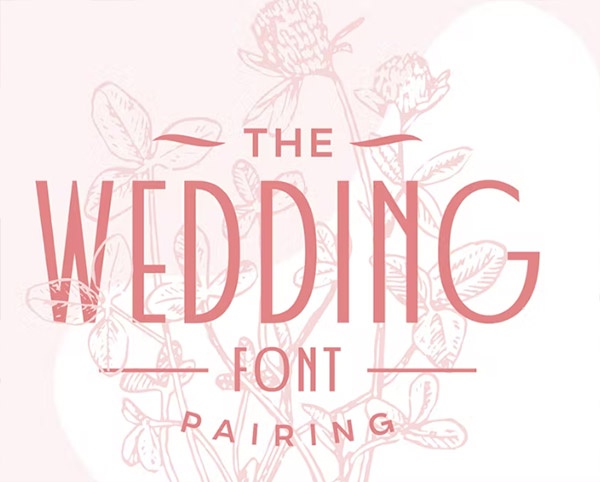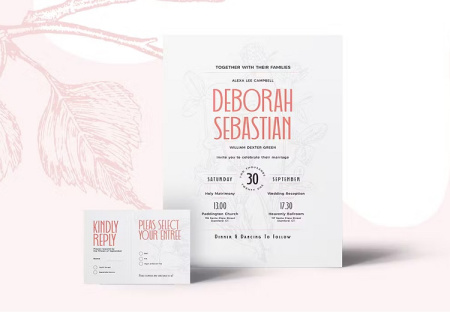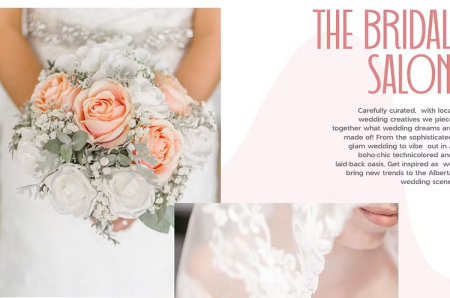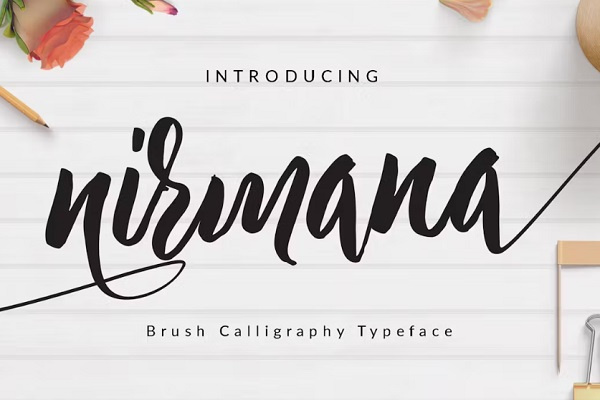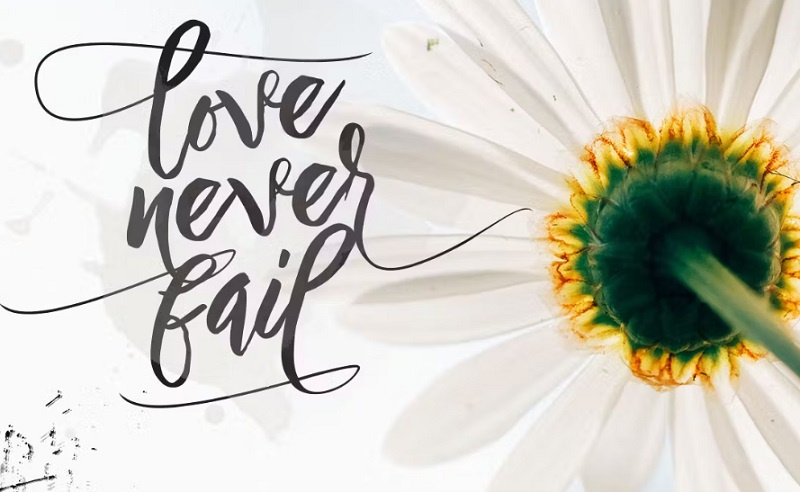
دانلود 4 فونت برای کارت های عروسی آپدیت جدید wedding font
دانلود فونت کارت های عروسی wedding font
دانلود فونت های کارت دعوت عروسی
featherly font wedding font نام این مجموعه فونت های کارت عروسی می باشد.بی شک یکی از نکات مهم در طراحی های مختلف فونت مورد استفاده می باشد مخصوصا اگر آن طراحی مربوط به روز عروسی باشد !featherly یک فونت خوشنویسی دست کشیده می باشد که برای طراحی های کارت های عروسی،آلبوم و ژورنال های عروس،دعوت نامه ها،کارت های تبریک و سایر مراسم شادی شما ساخته شده است.برای دانلود فونت کارت های عروسی به ادامه مطلب مراجعه نمایید.
فونت انگلیسی برای کارت دعوت عروسی
فونت انگلیسی کارت عروسی Deryttha
دانلود فونت انگلیسی عروسی Deryttha
فونت انگلیسی برای کارت دعوت عروسی
دانلود فونت انگلیسی برای کارت دعوت عروسی
در این مطلب شاهد یک فونت زیبا کارت عروسی می باشید. از این فونت انگلیسی ویژه طراحی و تدوین عروسی می توانید در طراحی انواع کارت به خصوص کارت عروسی استفاده کنید.
فونت کارت عروسی
فونت انگلیسی کارت دعوت عروسی در جی اف ایکس دانلود
✅ شامل 4 مجموعه فونت انگلیسی مختلف
✅ فونت 1 : featherly font wedding font
✅ فونت 2 : Wedding Font Pairing
✅ فونت 3 : Deryttha
✅ فونت 4 : Nirmana Brush Font Wedding
✅ مناسب طراحی کارت دعوت عروسی، نامزدی و ...
✅ طراحی جدید و زیبا